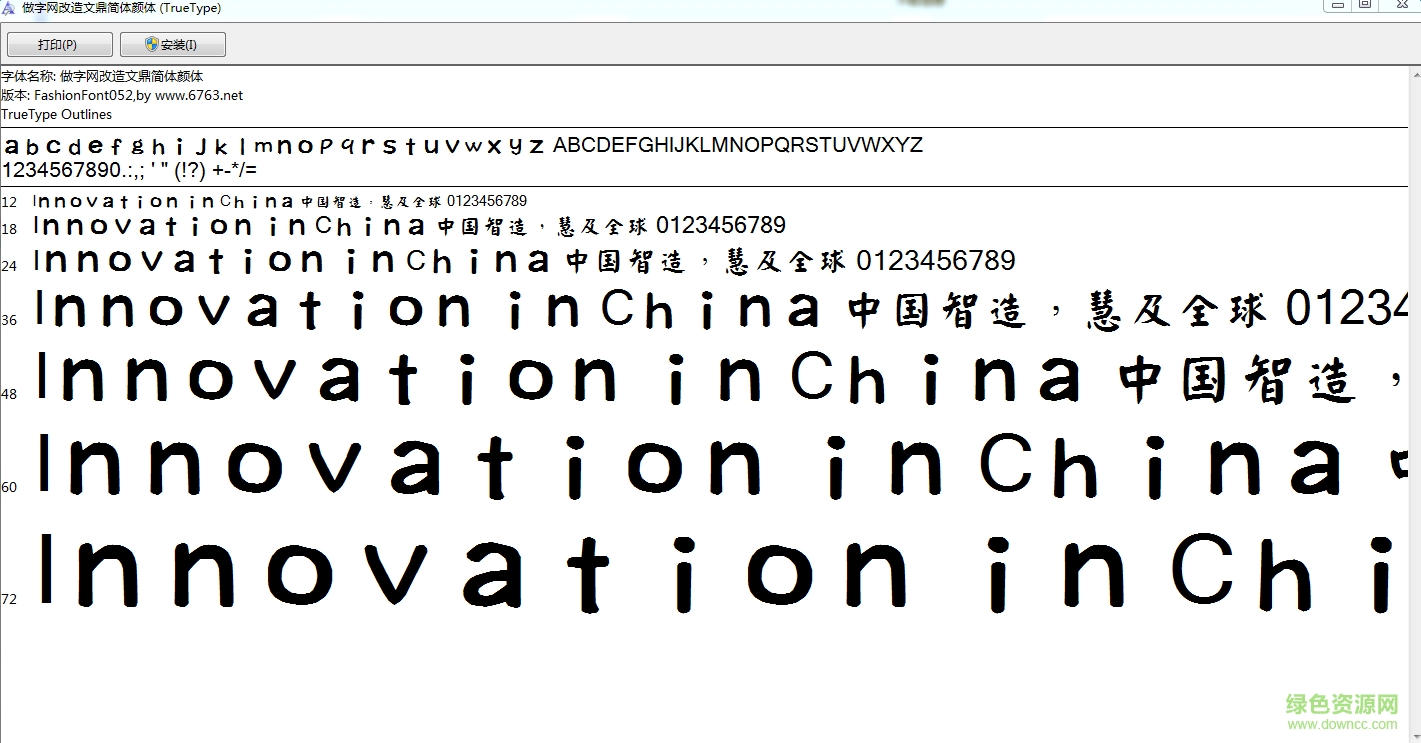
軟件介紹 軟件標簽: fashion字體 顏體字體 fashionfont052是什么字體?這款字體全稱為做字網改造文鼎簡體顏體,清晰秀麗,線條堅實又富有彈性,用來排版可以給人全新的閱讀感受,歡迎大家免費下載!字體的選擇1.古樸、經典的個性就選襯線體2.現(xiàn)代、簡約的個性就選無襯線體來參照顏體字體推薦方正顏體字體 授權:免費軟件 WinAll, WinXP, Win7, Win8大小:9.3M語言:中文方正顏體簡體字體是一款穩(wěn)重醒目的方正字體,結構嚴謹,厚重大氣,兼具術性和實用性,可用于網頁設計、古籍書刊、雜志海報等各個方面,需要的朋友快來下載吧!顏體字體介紹唐書法家顏真卿的字體風格。其書法初學褚下載地址田氏顏體字體 授權:免費軟件 WinAll, WinXP, Win7大?。?.8M語言:中文田氏顏體大字庫字體是一款簡體字體,筆鋒銳利,端正大氣,效果出色常常應用于藝術設計和平面設計領域,需要的朋友快來綠色資源網下載!字體安裝方法方法一:控制面板/字體/文件/安裝新字體;方法二:直接將字體復制到下載地址fashionfont052 by字體安裝方法方法一:控制面板/字體/文件/安裝新字體;方法二:直接將字體復制到C:\WINDOWS\Fonts。方法三:針對win7系統(tǒng),用戶只需選中字體右鍵安裝即可。 軟件截圖 上一張下一張(1 / 1) 安裝詳細截圖 猜你喜歡 顏體字體 顏體字體 顏體是一款極具古樸厚重韻味的字體,這里匯集了各具特色的顏體字體,每款字體都有著顏體豐腴雄渾、骨力遒勁的魅力,因此顏體也深受廣大書法家的喜愛,下面有綠色資源網小編為大家提供顏體字體下載大全,感興趣的朋友歡迎來綠色資源網下載體驗! 查看更多>> 經典簡顏體字體 2.44M/中文/1.2/下載 tianshi-yanti字體 2.92M/中文/5.0/下載 全真顏體簡體字體 4.88M/中文/2.5/下載 fashionfont052 by字體 2.44M/中文/2.0/下載 刻石錄顏體字體 8.53M/中文/5.7/下載 顏體字體下載大全 52.01M/中文/1.6/ttf下載 其他版本下載 標題 大小 更新日期 下載 下載地址 電腦版 fashionfont052 by字體 點擊報錯 軟件無法下載或下載后無法使用,請點擊報錯,謝謝! 關閉報錯反饋 請描述您所遇到的錯誤,我們將盡快予以修正,謝謝! *必填項,請輸入內容 本類最新 dreamweaver字體庫 首爾南山體字體 v1.06 官方版 潮字社風云簡ttf 潮字社凌渡鯤鵬簡體字體 潮字社曾玉波手書簡字體 微博慧心字體 相關文章 ASP:一個網站空間多個域名訪問 初學ASP編程易犯的一個錯誤要注意 ASP連接MSSQL的錯誤: 拒絕訪問 ASP實例教程:Form集合 徹底杜絕PHP的session cookie錯誤 簡單入門ASP變量 用戶評論 熱門評論 最新評論 發(fā)表評論 查看所有評論(0) 昵稱: 請不要評論無意義或臟話,我們所有評論會有人工審核. 字數(shù): 0/500 (您的評論需要經過審核才能顯示)